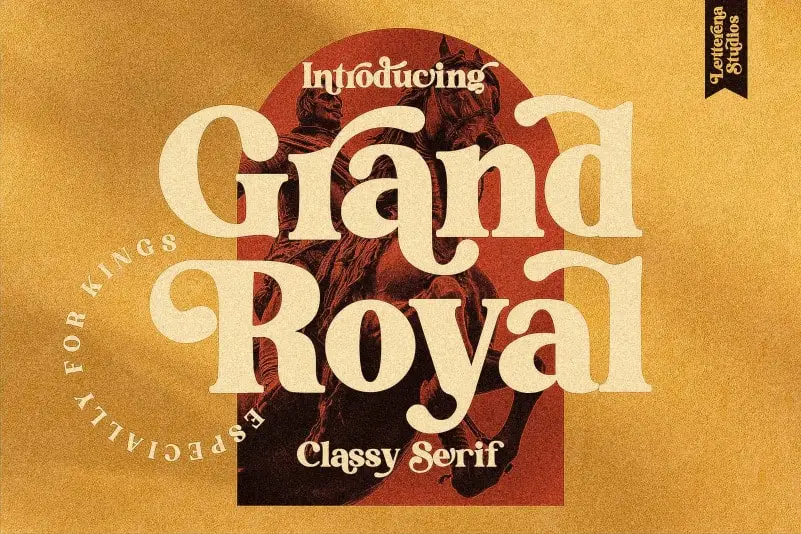
Grand Royal Serif Font – Fonte Grátis
Grand Royal Serif Font
Grand Royal Serif é uma fonte serif bold e elegante que oferece uma versatilidade impressionante. Embora sua simplicidade seja sofisticada, ela se destaca com estilo único capaz de dar vida a qualquer projeto gráfico. Suas linhas robustas criam um equilíbrio perfeito entre seriedade e encanto, tornando-a perfeita para criar cartões de aniversário elegantes ou até mesmo postagens sociais impactantes. Seu uso não apenas enriquece sua paleta de fontes, mas também amplia suas possibilidades criativas, permitindo que você crie designs memoráveis e sofisticados em uma variedade de mídias. Com Grand Royal Serif Font, designers podem explorar seus próprios estilos únicos ao criar cartões de visita, portfolios pessoais ou até mesmo capas para revistas. Seja no design editorial, na criação de websites com um visual profissional ou simplesmente quando desejar adicionar uma textura elegante aos seus layouts digitais – Grand Royal Serif oferece a versatilidade necessária. Se você está procurando por uma fonte serif que seja mais do que apenas uma escolha estética, então essa é sua fonte ideal. Com um toque de sofisticação e uma atitude audaciosa, Grand Royal Serif pode revolucionar seu design digital. Aproveite a beleza única dessa fonte para enriquecer suas criações.